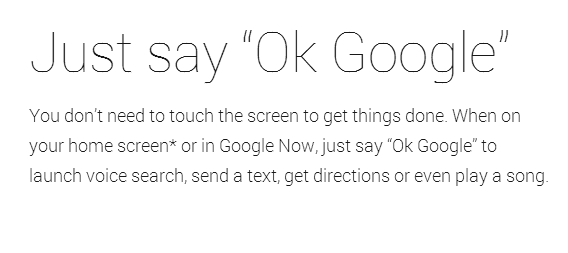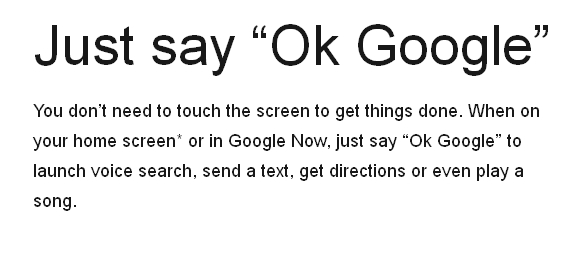
Chrome: Probleme mit Antialiasing der Webfonts
Chrome (Version 30.0.1599.101 m) versagt wenn es ums Antialiasing (Kantenglättung) diverser Webfonts geht. Firefox arbeitet dabei fehlerfrei, anbei 2 anschauliche Screenshots im Vergleich:
Der Ursprungstext: http://www.android.com/versions/kit-kat-4-4/
Ja ich weiß, es ist ein Luxusproblem... aber mich stört es schon ein wenig. Ist das normal bei Chrome?
Hab recherchiert und anscheinend nimmt Chrome die Clear Type Settings vom System als Referenz. Hab das Cleartype probeweise geändert aber im Chrome ändert sich nichts.
Würde mich auch sehr Interessieren an was es liegt, denn unter Firefox sieht das ganze sehr viel besser aus : (
Prima das man mal was anderes findet:p habs auch gerade gesehen, bei Chrome sieht es schlechter aus:mad:
erstes Bild ist von Chrome Version 30.0.1599.101 m zweites Firefox 25